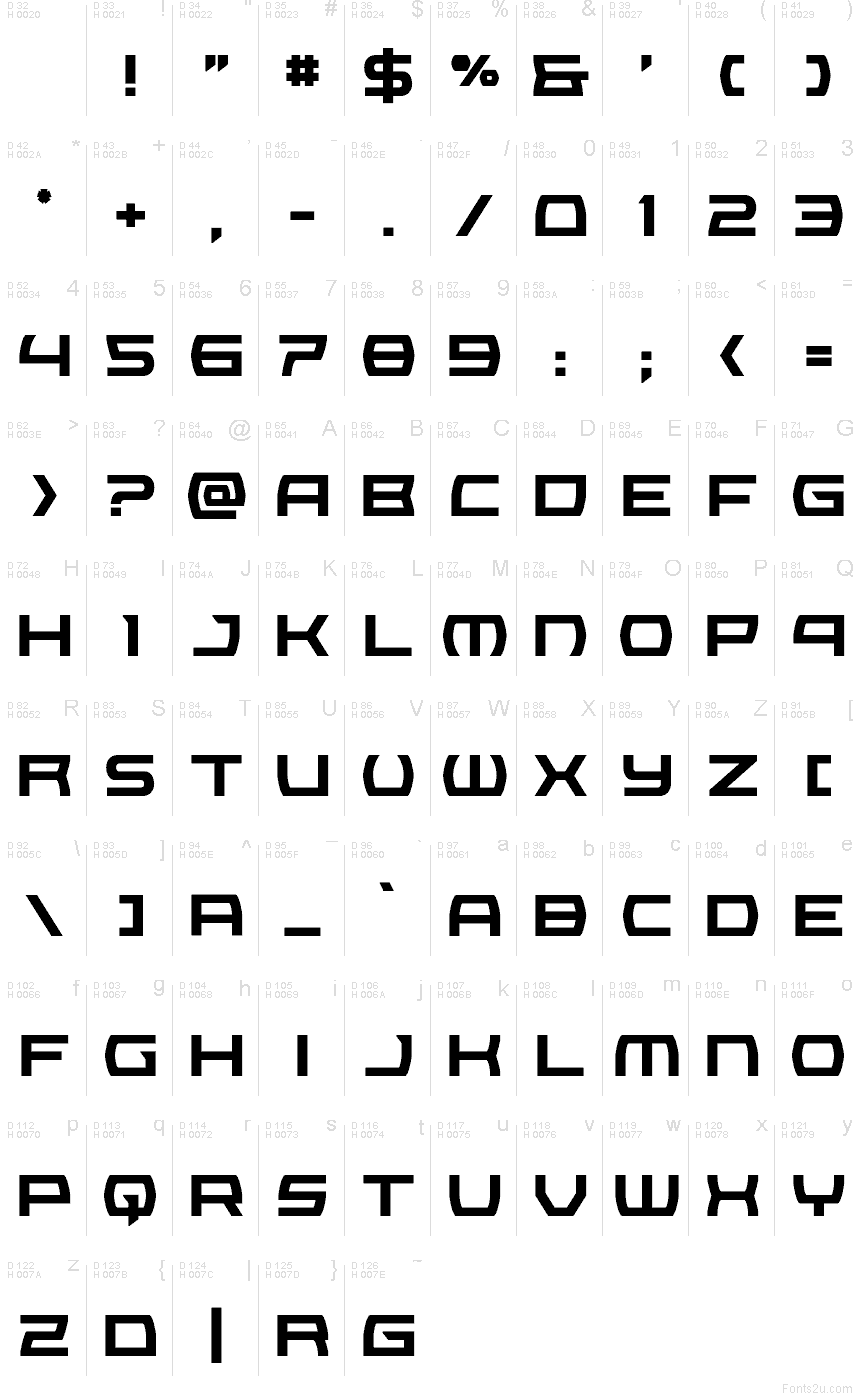
Icemaster Bold von Iconian Fonts ist eine kostenlose, futuristische Display-Schrift für Großbuchstaben mit einer kühlen, technischen Ausstrahlung. Die Buchstaben sind breit und blockartig, doch die abgerundeten Innenschnitte und Ecken nehmen ihnen die Schwere. Das verleiht dem Alphabet einen schnittigen Sci-Fi-Rhythmus, der an Eis, Maschinen und Retro-Weltraumgrafiken erinnert.
Diese kostenlose Schrift passt perfekt zu Gaming-Logos, Tech-Postern, Album-Covern, Titelkarten und E-Sport-Branding, wo kurze Wörter eine markante Silhouette benötigen. Sie eignet sich auch hervorragend für Cover-Zeilen und Monogramme, da die Großbuchstaben zu kräftigen Formen verschmelzen, die durch ihre Rundungen auch in großen Schriftgrößen lebendig wirken.